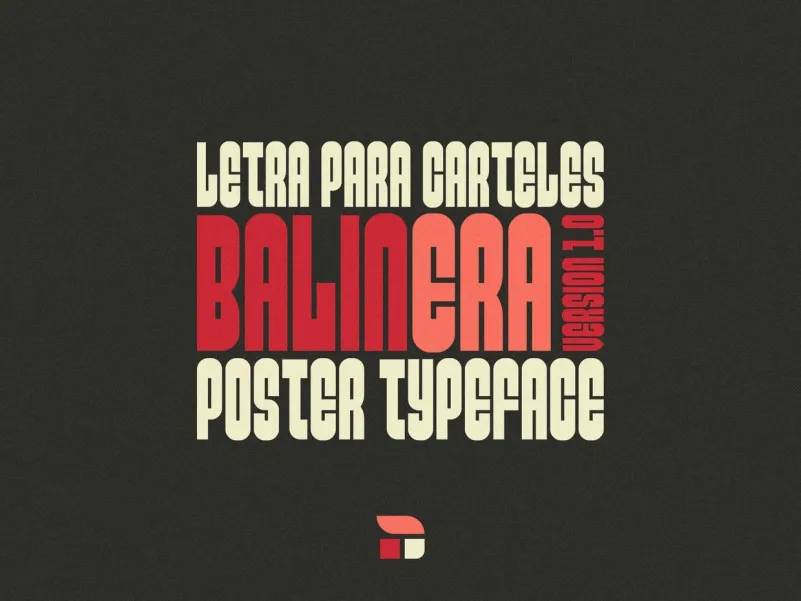
Balinera Font
A Balinera Font é uma escolha perfeita para quem procura um tipo moderno e poderoso que se destaca no cenário das fuentes display. Ela foi criada pela Nima Type, especializada em produzir tipos de letra com múltiplas línguas, permitindo a utilização global sem problemas. Esta fonte é apelidada como um tipo masculino forte e moderno, ideal para criar textos curtos que podem ser inspiradores ou expressar lemas políticos fortes. Se procura dar mais dinamismo ao seu layout gráfico, a Balinera pode ser combinada com outros tipos de letra elegantes ou rústicos, criando um visual atraente e vibrante. Ideal para uso em logotipos, banners ou qualquer outro aplicativo que exige uma presença forte na cena digital contemporânea.